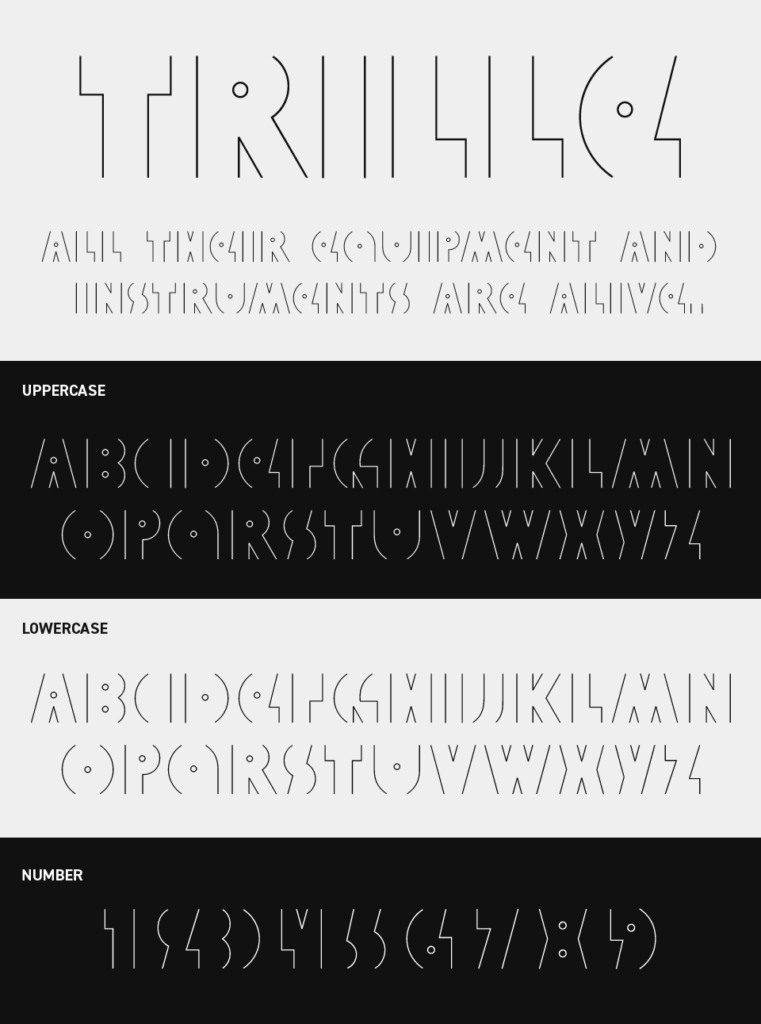
Ductile Display Font
Trilleフォントは、極細のアウトラインで構成され、かつ上下のラインを削除している幾何学的でユニークが印象的なデザインフォントです。
直線や円弧を組み合わせたシンプルな字形が、未来的でミニマルな雰囲気を生み出しています。
軽やかで繊細なラインが空間に余白をつくり、一見読めなさそうな文字なのに、見ているとだんだんと読めてくるようになる面白みのあるフォントです。